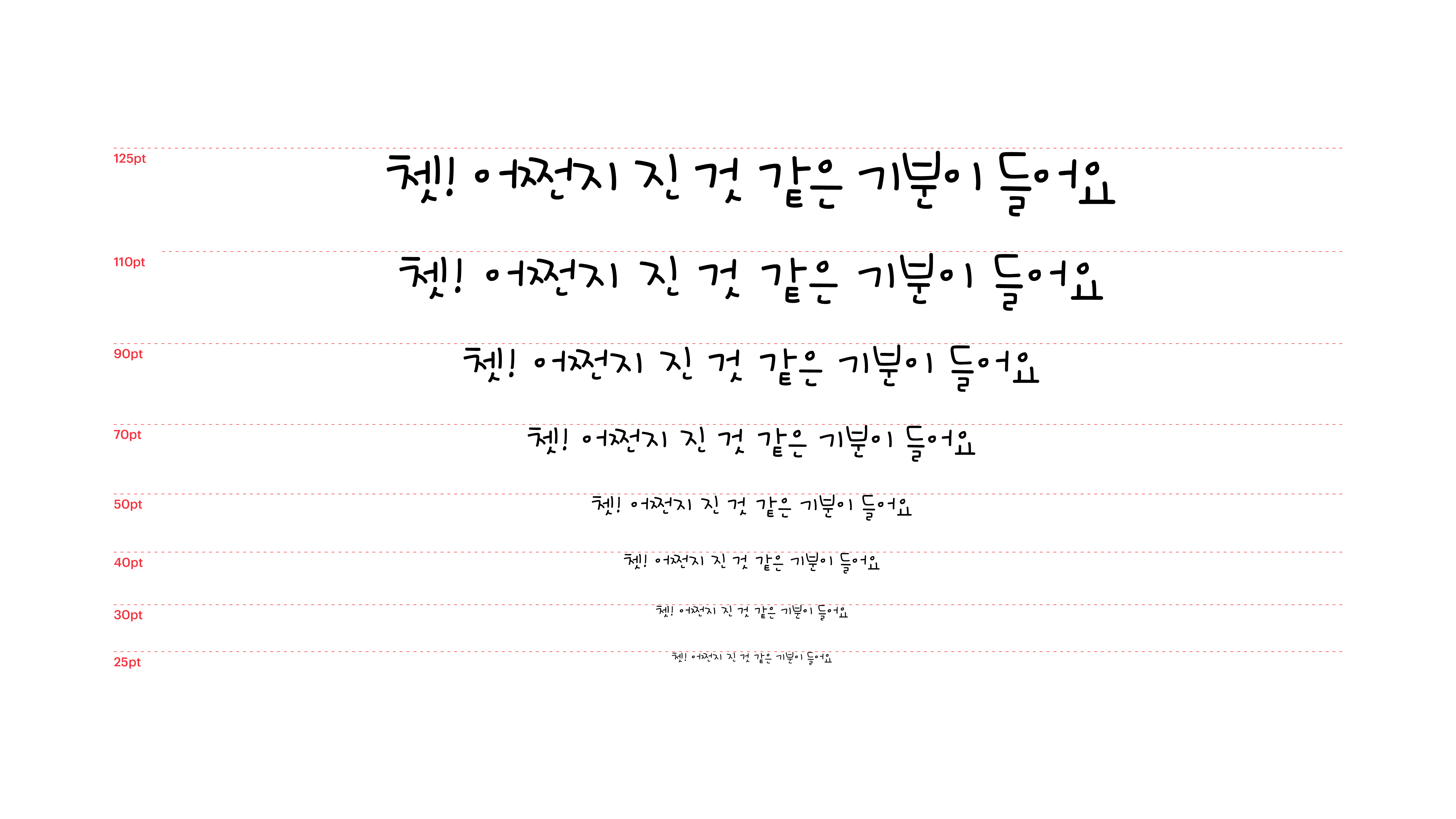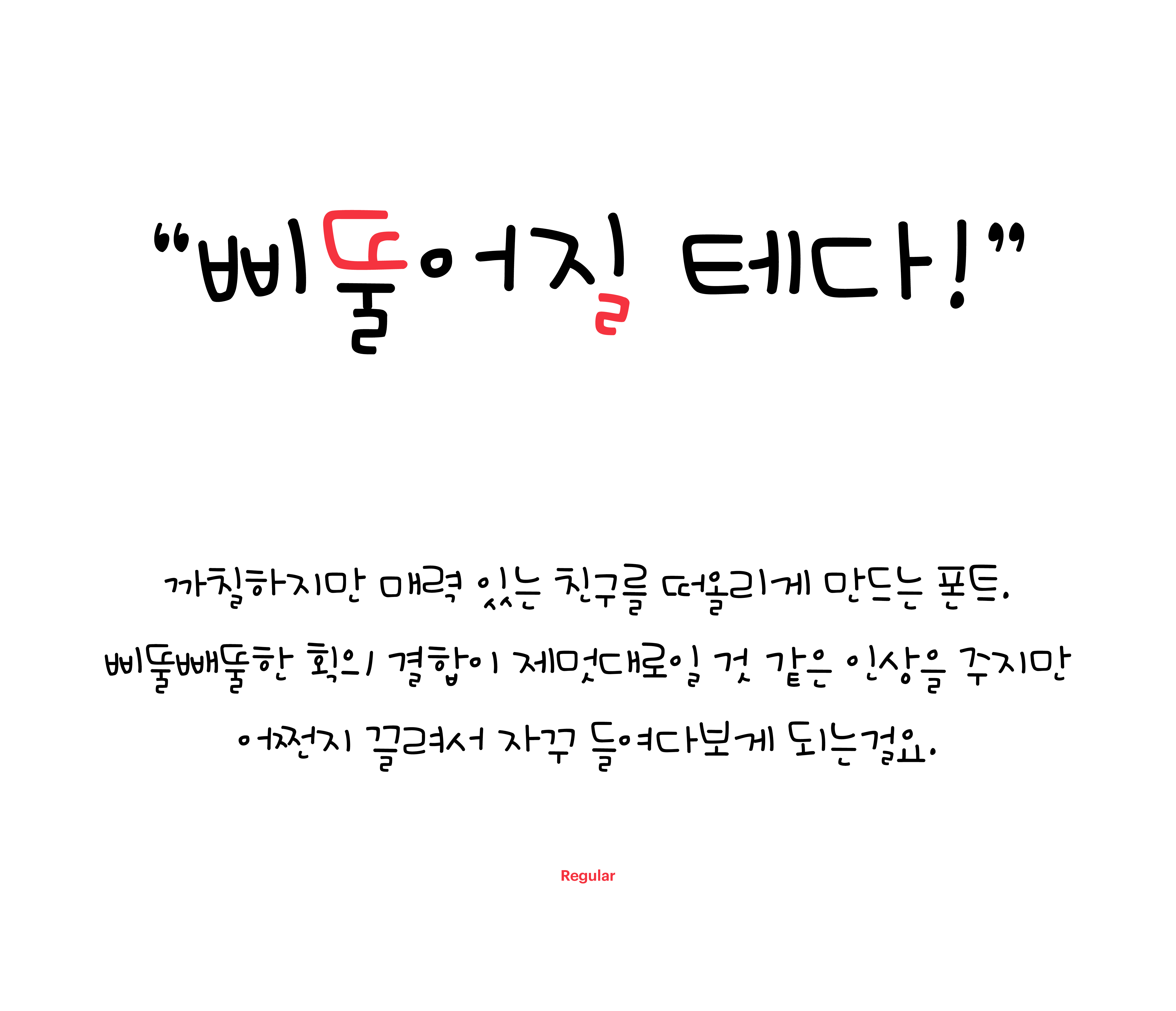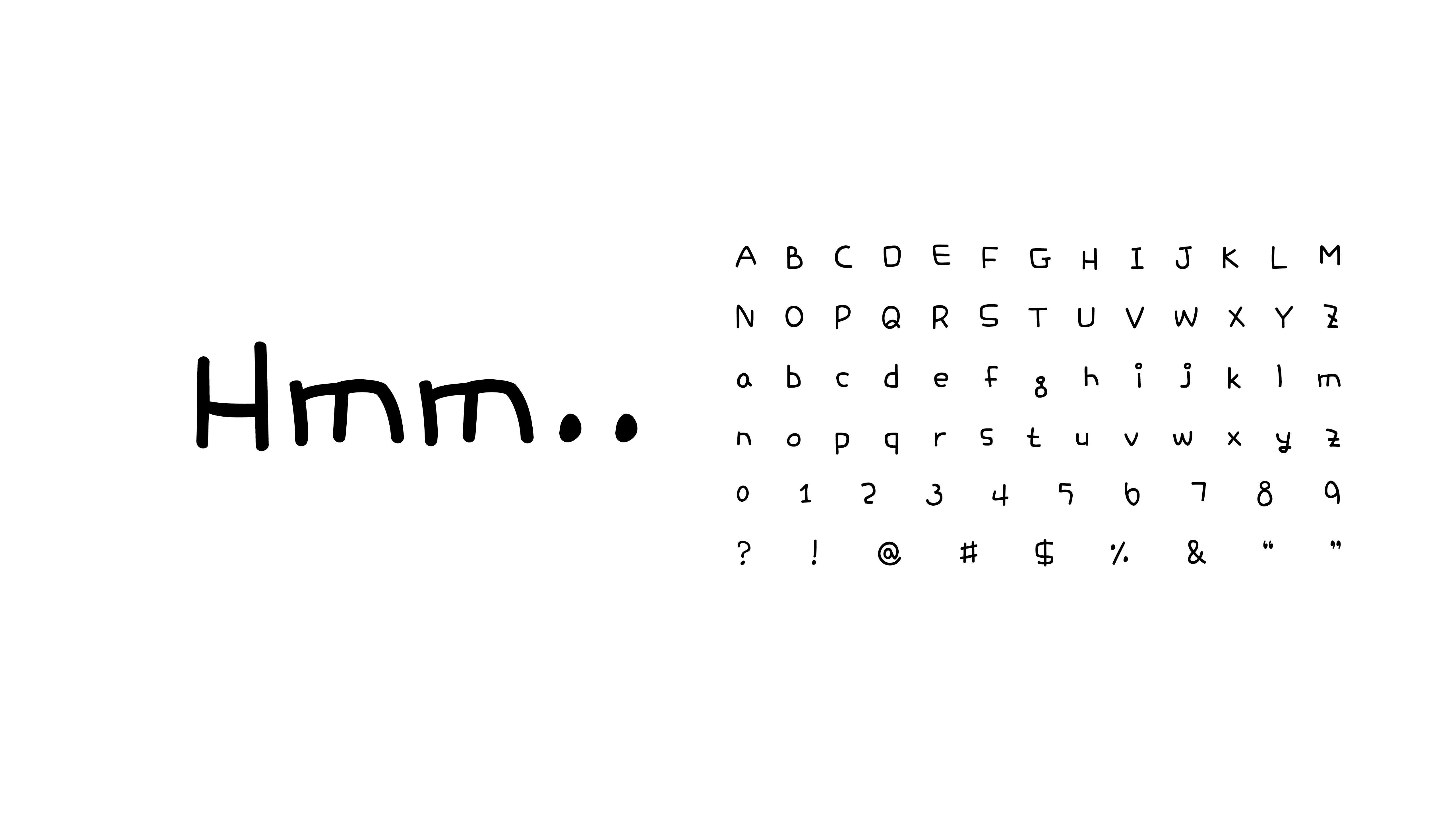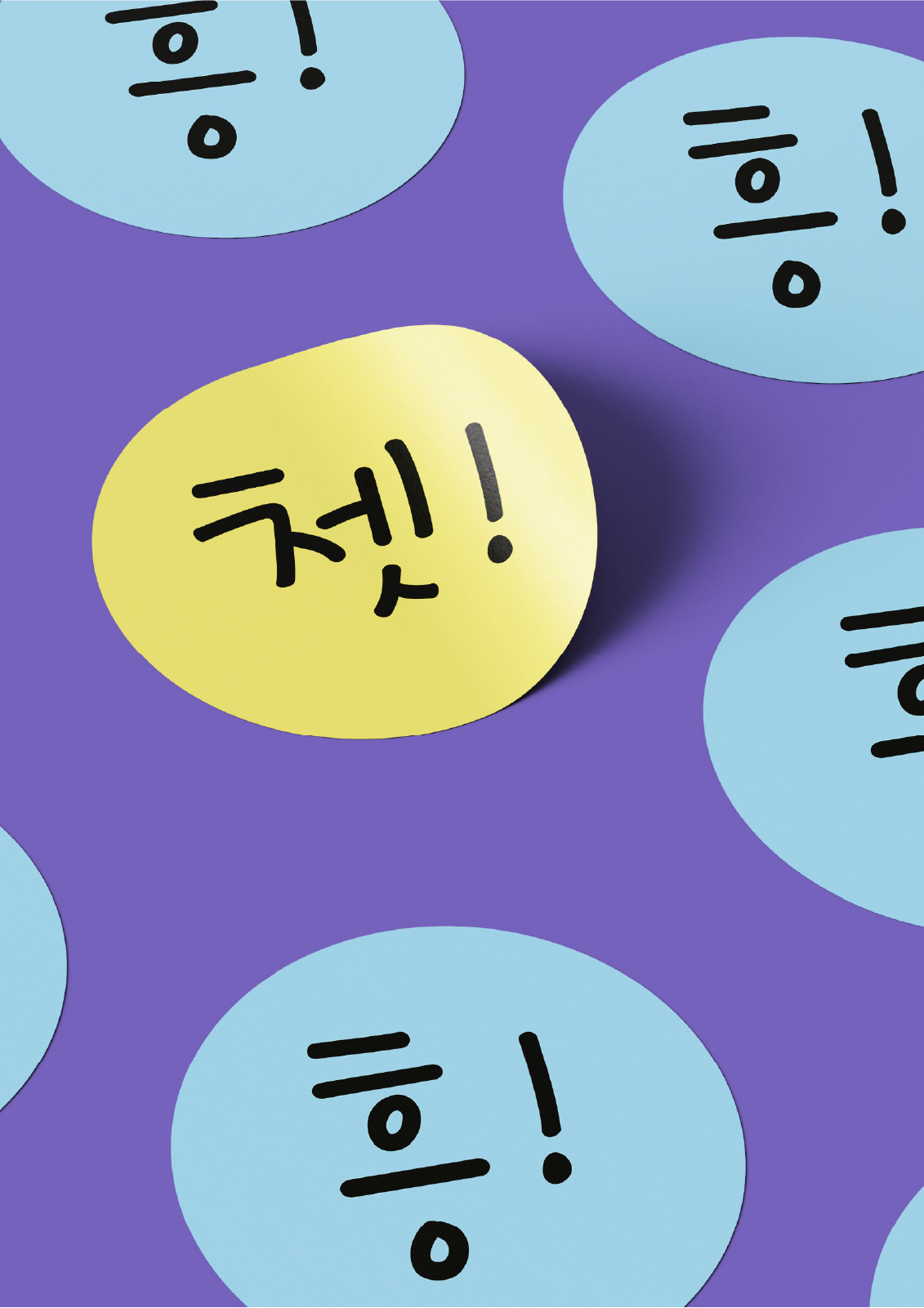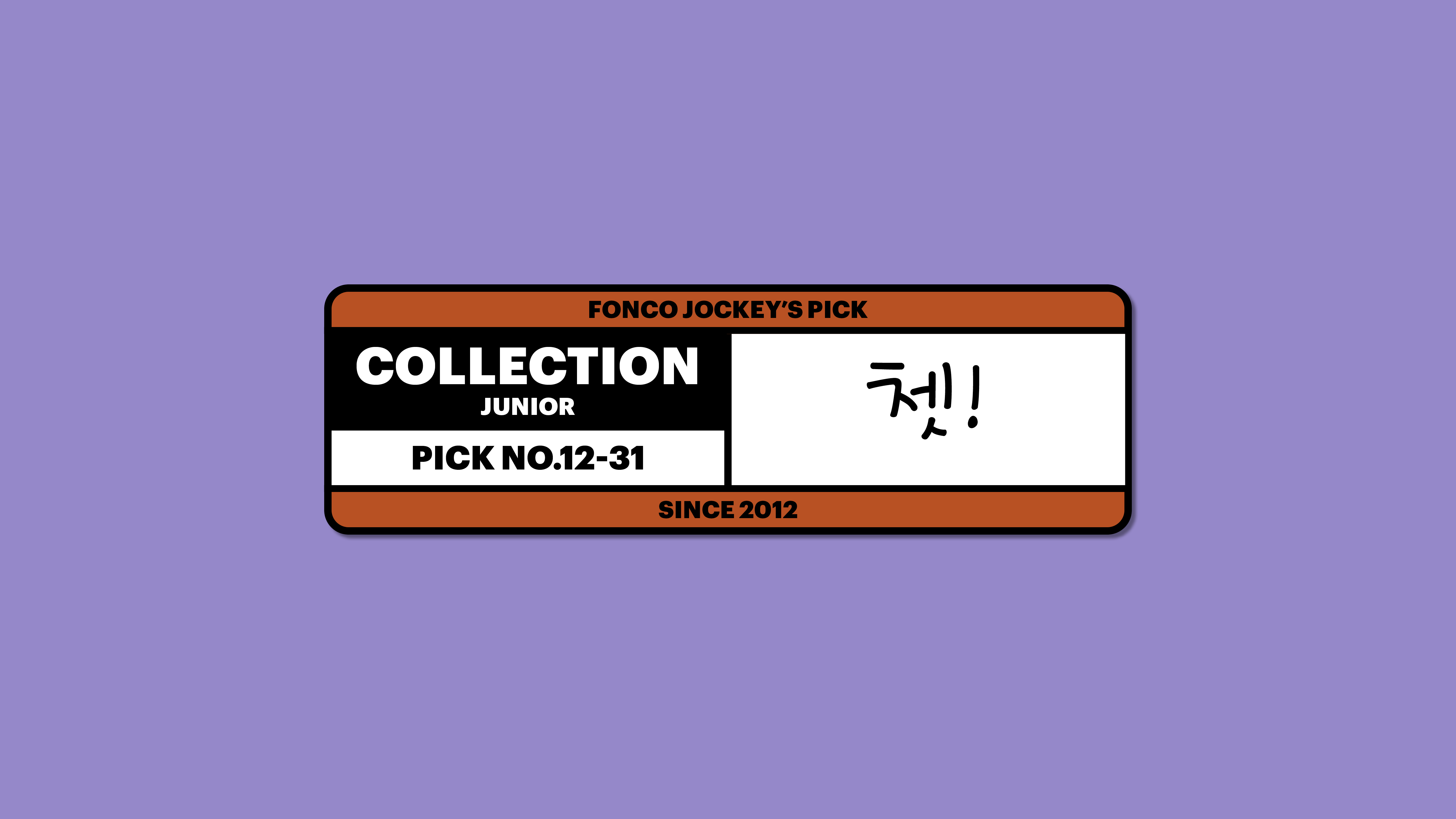
쳇!
Yoon 쳇!
까칠하지만 매력 있는 친구를 떠올리게 만드는 폰트입니다. 얇고 가느다란 획이 예민하게 배치되어 차가운 인상을 주지만 어쩐지 자꾸 들여다보게 되는걸요. 쳇! 어쩐지 진 것 같은 기분이 들어요. “집에 같이 가지 않을래?” 이미 손으로는 메시지를 보내고 있고.